涂鸦艺术正在慢慢走近大众,在外国,人们可能会发现昨天好好的地铁车厢今天突然变成了一个流动的涂鸦展览会,上面画满了五颜六色的图案。涂鸦是种不容错过的城市美学。来源于街头,涂鸦是一种手写风格,带有强烈的划痕和手绘特征,而且你可以通过使用这些字体来为你的设计添加相同的感觉,不如一起来看看下面图片字体吧。
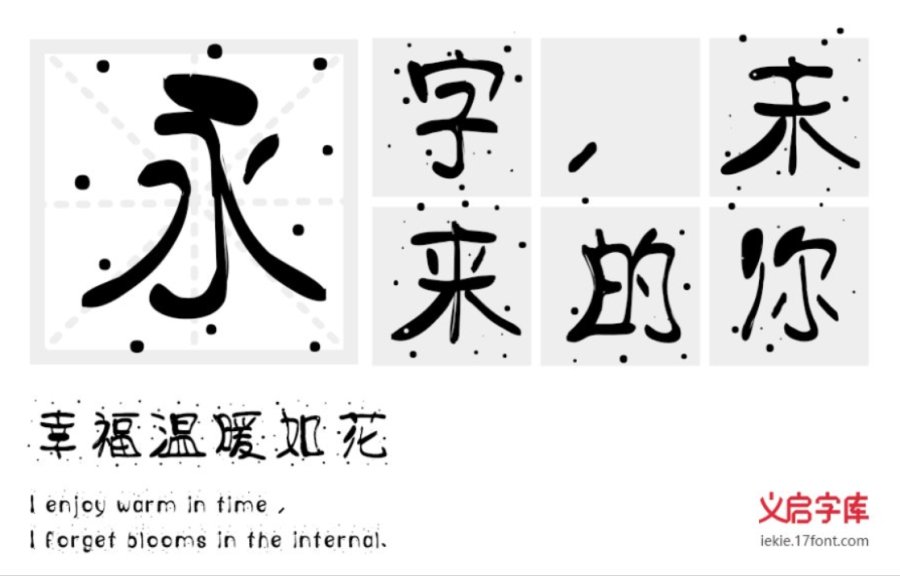
这款极具个性特色的字体叫做“撒盐体”。像极了大厨均匀撒在香喷喷的菜肴上的盐粒。这款字体字形相当时尚,具有厚实的弯曲质感和传统的涂鸦氛围。适用于短视频特色字、H5文字、游戏、广告设计、动漫等创意设计领域。
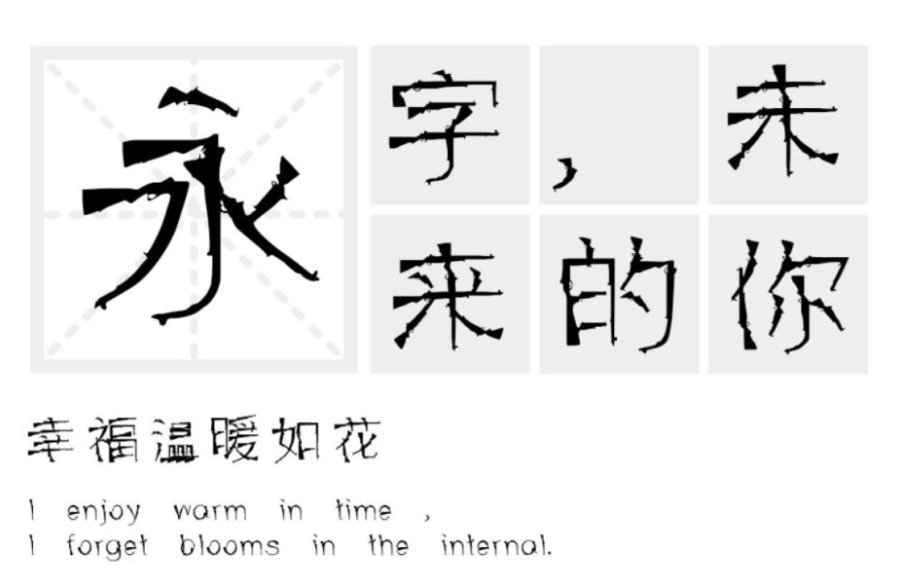
通常字形中的点、撇、捺、钩、提等笔画各具面目,而这款“汉标老枪体”笔画运用了老枪图形元素来构建,把这些笔画做成了老枪,概括为飘逸的老枪,并且使左右舒展的笔画尽量对称,最大限度地简化笔画老枪造型不失方正大方。用这种字体可以为设计制作出独特的外观。适用于短视频特色字、漫画、游戏等创意设计领域。